I Am Yours Lettering. Calligraphic Inscr
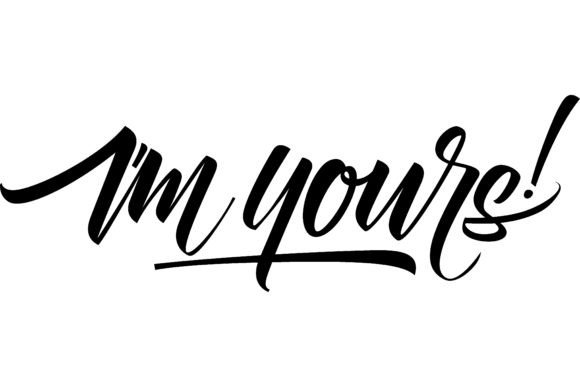
Trouver les bons éléments de conception peut être un défi, mais I Am Yours Lettering. Calligraphic Inscr propose une collection exceptionnelle qui rehausse instantanément votre travail.
Conçu avec précision, I Am Yours Lettering. Calligraphic Inscr offre des vecteurs nets, une typographie fluide et une licence commerciale pour une tranquillité d'esprit.
Que vous créiez des produits POD (impression à la demande), des invitations de mariage ou des visuels pour les réseaux sociaux, I Am Yours Lettering. Calligraphic Inscr est un choix idéal.